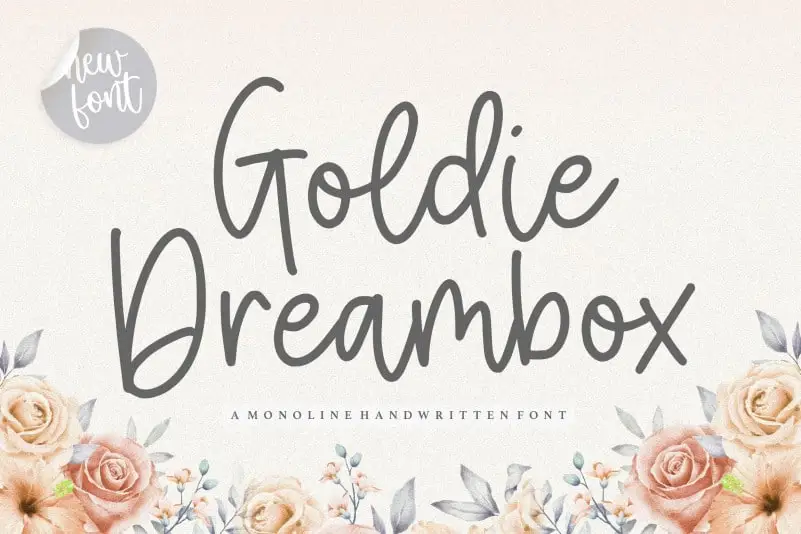
Goldie Dreambox Monoline Handwritten Font – Download Grátis
A fonte “Goldie Dreambox Monoline Handwritten” é perfeitamente adequada para estilos criativos que valorizam uma mão-dura e elegante no mesmo tempo. Este estilo handwritten proporciona um toque suave e personalizado, ideal para aplicar em pacotes de produtos, projetos de marca e revistas, seja por suas características distintas e agradáveis ou usadas para destacar o texto sobre qualquer fundo. Perfeita para o seu projeto social ou sua própria publicação pessoal no Instagram ou Facebook. Ela também é perfeitamente adequada para usar em convites de casamento, dando um toque especial à decoração da cerimônia e às chamadas para a festa. E se você está buscando expressar uma ideia específica através do texto, esta fonte é perfeita para criar um visual único e memorável. Sem dúvida, ela trará vida ao seu design com sua simplicidade e elegância inconfundíveis. Esse designer talentoso, balpirick, trouxe a nós essa fonte que combina a essência da escrita cuidadosamente redigida com a liberdade do estilo handwritten. Ela é uma escolha perfeita para quem busca um tom de texto atencioso e elegante para seus projetos, seja para destacar produtos ou para criar uma identidade visual única e memorável.